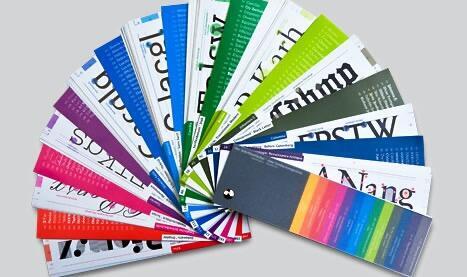
Der neue Schriftfächer zeigt auf einer Blattseite charakteristische Buchstaben der betreffenden Schrift. Die Besonderheiten werden hervorgehoben und benannt. Anhand dieser Buchstabenfolge werden gleichzeitig die horizontalen Größenverhältnisse der Schrift vermessen. Weiterhin werden die Hauptbuchstaben (A bis Z und a bis z), die Ziffern und einige Satzzeichen abgebildet. Letzlich werden folgende Informationen gelistet: Schriftentwerfer; Jahr des Erscheinens der Schrift; Schriftname im Schriftmenü; Anzahl der Schnitte, die der Zürcher Hochschule der Künste und der Zürcher Fachhochschule zur Vergügung stehen (!); Klassifizierung nach DIN 16 518; Herkunftsnachweis.
Auf der Rückseite wird das Wort »Typografie« in 24 Punkt wiedergegeben. Danach folgt ein Text, der den Nutzer die Schrift in Lesegröße beurteilen lässt. Diese Texte sind gleichzeitig ein Glossar typografischer Begriffe, wie zum Beispiel Schattenachse, Duktus oder Unterlänge. Die Schnitte, die den beiden Schulen vorliegen, sind hier ebenfalls abgebildet.
Im Vorfeld werden Literaturhinweise genannt und Internetverweise gegeben. Auf fast zwanzig Blatt wird über Terminologie der Schrift, Schriftlinien/-höhen, Schriftproportionen, Strichstärken, Schriftbreiten, Schriftlagen, Monospace-Schriften, Schriftschnitt/-familie, Schriftsippe/Hybridschriften, Schriftmischung, Geviert, geviertbasierende Leerräume, geviertbasierende Strichlängen, OpenType-Schriftformat und die DIN-Klassifikation 16 518 informiert.
Untertitel: Eine Entdeckungsreise
Autor(en): Samuel Marty, Richard Frick